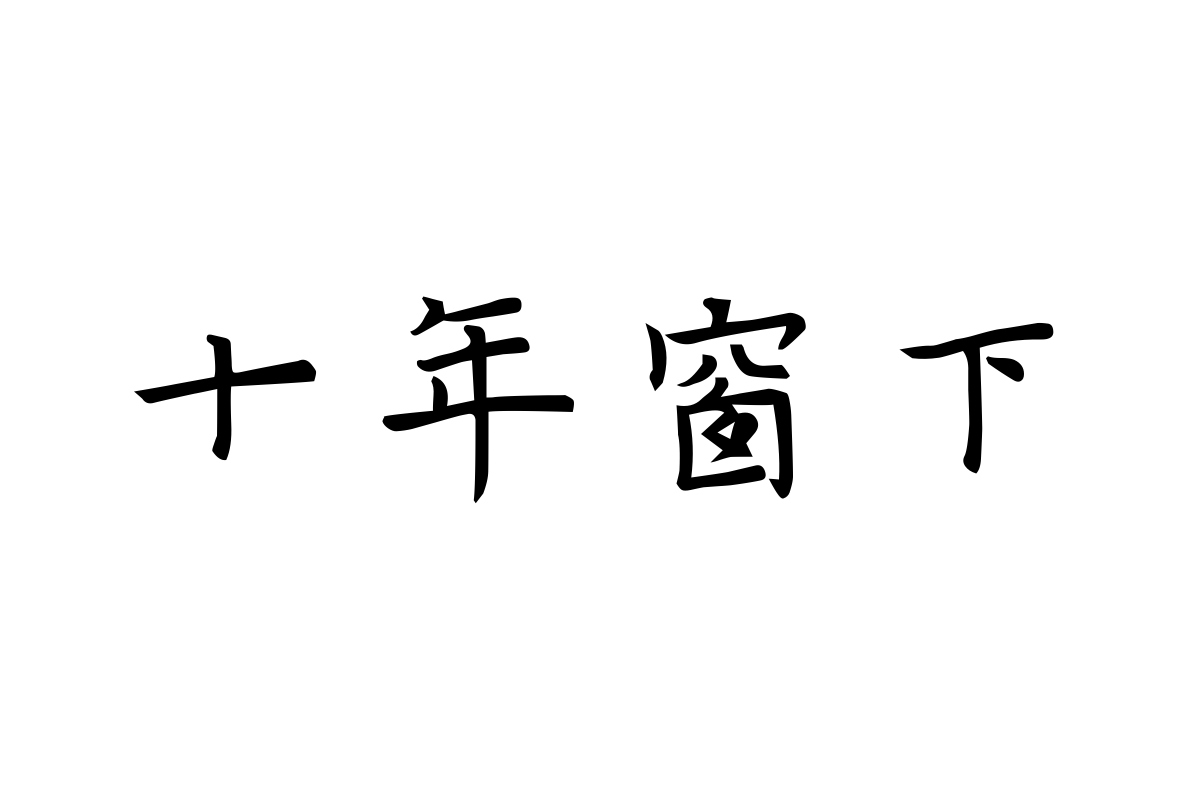
仓耳古风楷书是一套具有古典韵味的书法字体,它以传统的楷书为基础,融入了更多的艺术元素和装饰性细节。这种字体的特点是线条流畅、结构严谨,同时又不失灵动和变化。
仓耳古风楷书的特点包括:
1. 线条流畅:字体中的笔画线条流畅自然,没有过多的顿挫和转折,给人一种舒适和优雅的感觉。
2. 结构严谨:虽然线条流畅,但字体的结构却非常严谨,每个字都保持了一定的平衡和对称性,使得整个字体看起来既规整又富有层次感。
3. 装饰性强:在保留楷书基本形态的同时,仓耳古风楷书中还融入了一些装饰性的笔画和符号,如小篆、隶书等,使得整个字体既有古典韵味,又不失现代感。
4. 艺术性高:仓耳古风楷书不仅仅是一种文字表现形式,更是一种艺术创作。书法家们通过自己的理解和技巧,将楷书与各种艺术元素相结合,创造出独特的视觉效果。
总的来说,仓耳古风楷书是一种集传统与现代、艺术与实用于一体的书法字体,适合用于书写正式文件、诗词歌赋等多种场合。